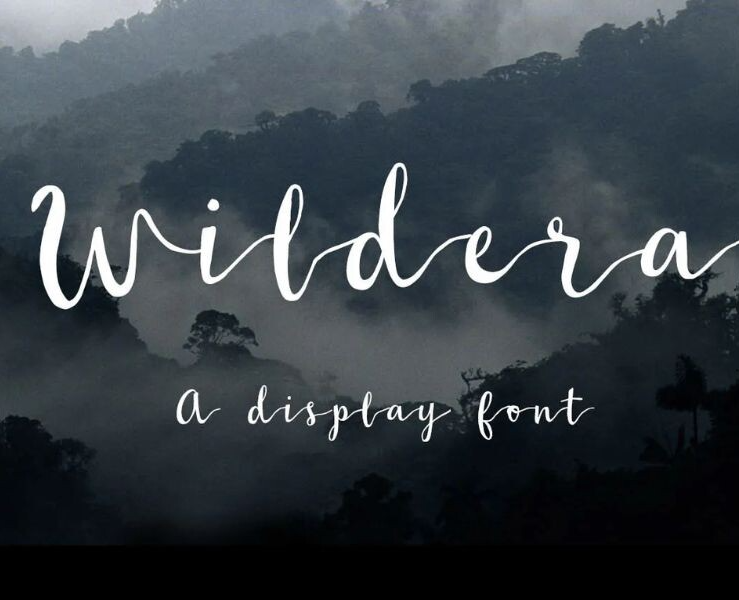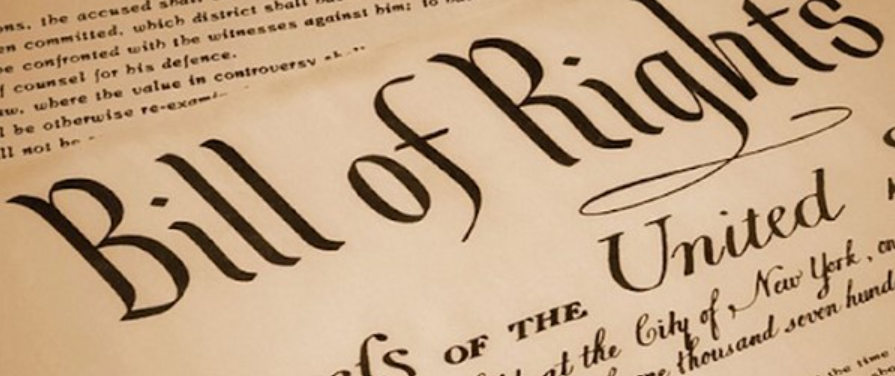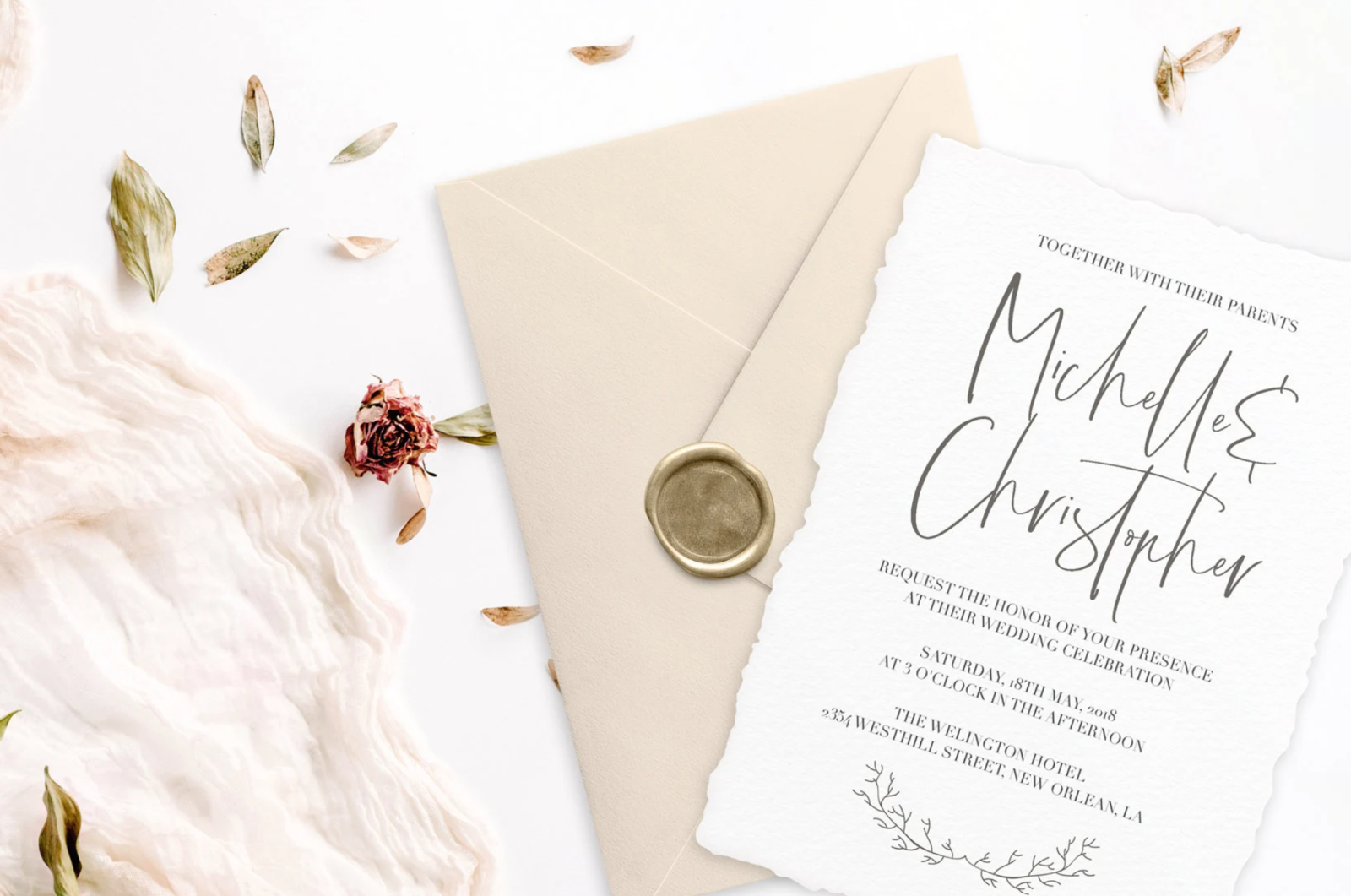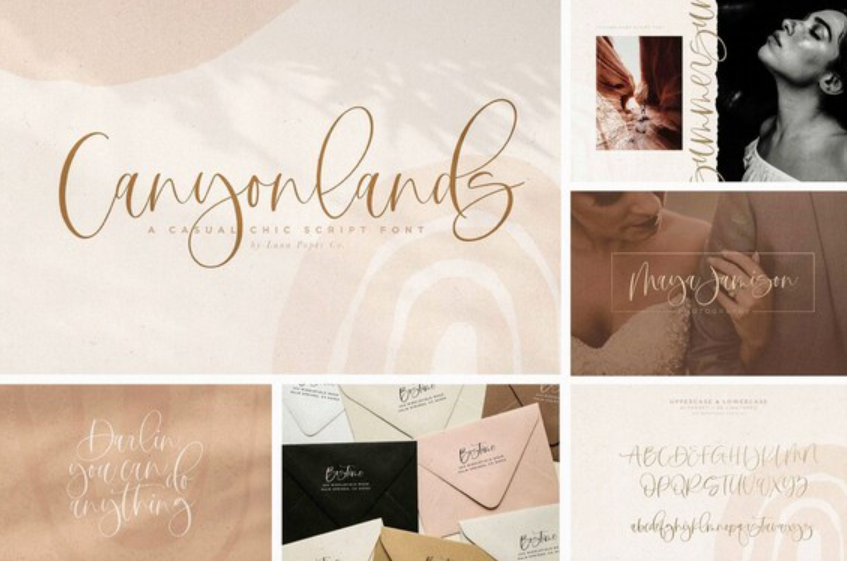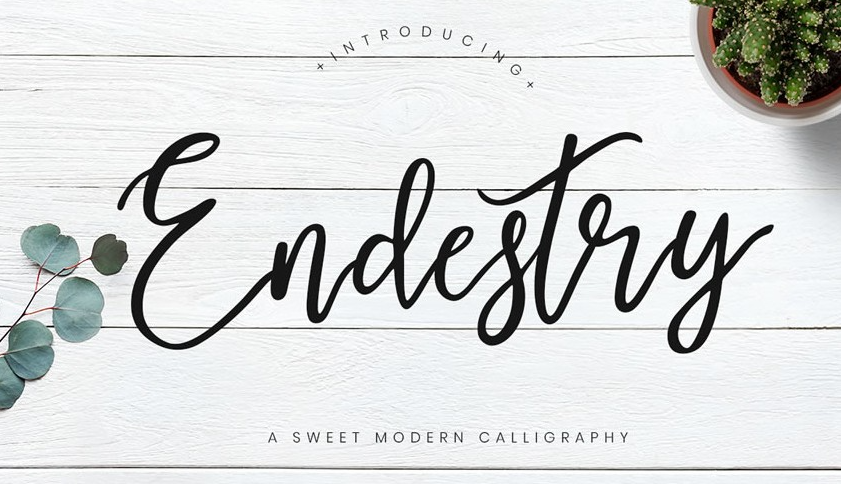
Khám Phá Font Chữ Calligraphy: Nghệ Thuật Ẩn Chứa Trong Từng Đường Nét
Bài viết sẽ mở ra hành trình khám phá về font chữ Calligraphy, giải mã nguồn cảm hứng nghệ thuật và cách mà từng nét chữ mang đậm giá trị sáng tạo, biến mỗi thiết kế thành một tác phẩm nghệ thuật độc đáo.
Font chữ không chỉ là công cụ truyền tải thông điệp mà còn là yếu tố nghệ thuật góp phần tạo nên cảm xúc và sự ấn tượng mạnh mẽ. Trong số rất nhiều phong cách font chữ hiện nay, Calligraphy – hay còn gọi là chữ thư pháp nghệ thuật đã và đang chiếm một vị trí đặc biệt vừa thể hiện nét tinh tế, vừa mang đến sự sang trọng cho các thiết kế. Bài viết dưới đây sẽ cùng bạn khám phá font chữ Calligraphy để tạo nên những thiết kế ấn tượng và chuyên nghiệp. Cùng tìm hiểu nhé!
1. Tìm hieur về font chữ Calligraphy
1.1. Định nghĩa
Font chữ Calligraphy hay còn gọi là chữ thư pháp nghệ thuật, là loại font mang phong cách viết tay với đường nét mềm mại, uyển chuyển và thanh lịch. Điểm đặc trưng của Calligraphy chính là sự tự nhiên trong cách vẽ nét chữ, thường được lấy cảm hứng từ nghệ thuật viết tay truyền thống của các nền văn hóa khác nhau. Mỗi chữ cái được tạo ra không hoàn toàn đồng nhất như các font số học truyền thống, mà mang đậm dấu ấn cá nhân của người nghệ sĩ, thể hiện sự tinh tế, sáng tạo và nghệ thuật.
So với các loại font chữ khác như sans-serif hay serif, Calligraphy nổi bật với nét nghệ thuật riêng biệt. Trong khi các font sans-serif thường được sử dụng cho thông tin hiện đại, gọn gàng, còn font Calligraphy lại hướng tới sự mềm mại, trữ tình và mang tính thủ công. Sự khác biệt này giúp Calligraphy trở thành lựa chọn lý tưởng cho các dự án cần tạo cảm giác sang trọng và tinh tế, chẳng hạn như thiệp mời cưới, logo thương hiệu cao cấp hay tiêu đề các ấn phẩm nghệ thuật.
1.2. Lịch sử hình thành của font chữ Calligraphy
Xuất phát từ nghệ thuật viết tay truyền thống của các nền văn hóa lớn như Trung Hoa, Ấn Độ hay phương Tây, Calligraphy từ lâu đã được tôn vinh như một hình thức nghệ thuật đòi hỏi sự tinh xảo và kiên nhẫn. Ở phương Đông, nghệ thuật thư pháp đã có từ hàng ngàn năm trước, với những nét chữ đầy uyển chuyển và linh hoạt được xem là biểu hiện của tâm hồn người viết. Các danh nhân, triết gia, họa sĩ cổ truyền không chỉ dừng lại ở việc truyền đạt thông tin mà còn truyền tải những giá trị tinh thần sâu sắc qua từng nét chữ.
Ngược lại, ở phương Tây, font chữ Calligraphy cũng phát triển mạnh mẽ qua các thời kỳ từ trung cổ cho đến thời kỳ Phục Hưng và hiện đại. Các nghệ nhân đã biến những nét chữ tay đơn giản thành nghệ thuật sống động, mang đậm phong cách cá nhân và cảm hứng sáng tạo riêng biệt. Sự giao thoa giữa văn hóa Đông – Tây đã tạo ra nhiều phong cách Calligraphy đa dạng, từ cổ điển đến hiện đại, từ trữ tình, nhẹ nhàng cho đến táo bạo, phá cách.
1.3. Đặc điểm nhận diện
Những đặc điểm nổi bật giúp nhận diện font chữ Calligraphy bao gồm:
Đường nét mềm mại: Mỗi nét chữ đều được cẩn thận thể hiện với sự uốn lượn, tạo nên cảm giác mềm mại và tự nhiên.
Tính nghệ thuật: Mỗi đường nét, mỗi chi tiết nhỏ đều mang đến giá trị nghệ thuật riêng biệt, khiến chữ trở nên độc đáo và khác lạ.
Biến tấu đa dạng: Không giống như các font số học, Calligraphy luôn thể hiện sự khác biệt nhỏ trong mỗi chữ cái, tạo nên vẻ đẹp “không hoàn hảo” nhưng đầy cảm xúc.
Ứng dụng đặc thù: Do nét chữ thường được tạo ra với hương vị nghệ thuật mạnh mẽ, Calligraphy thích hợp cho những thiết kế cần làm nổi bật thông điệp về sự trang nhã, tinh tế và độc đáo.
2. Ưu điểm và nhược điểm của font chữ Calligraphy
2.1. Ưu điểm của font chữ Calligraphy
Khi được áp dụng đúng cách, font chữ Calligraphy mang lại nhiều lợi ích cho thiết kế. Dưới đây là một số ưu điểm tiêu biểu:
Tạo sự sang trọng và độc đáo:
Font chữ Calligraphy giúp tạo ra sự ấn tượng mạnh mẽ ngay từ cái nhìn đầu tiên. Nét chữ mềm mại, tinh tế và đầy nghệ thuật làm cho các thiết kế trở nên sang trọng, phù hợp với những thương hiệu cao cấp hoặc các dịp đặc biệt như đám cưới, lễ kỷ niệm.
Mang đến tính nghệ thuật cao:
Với nguồn gốc từ nghệ thuật thư pháp truyền thống, Calligraphy không chỉ là font chữ mà còn là tác phẩm nghệ thuật. Sự tinh tế trong từng nét vẽ giúp truyền tải một thông điệp về sự sáng tạo, tinh thần và thậm chí cả cảm xúc của người thiết kế.
Phù hợp với các thiết kế tiêu đề và điểm nhấn:
Nhờ vào sự đẹp mắt và nổi bật của Calligraphy, các thiết kế sử dụng loại font này làm tiêu đề hoặc điểm nhấn sẽ thu hút sự chú ý của người xem một cách nhanh chóng. Điều này đặc biệt có lợi khi bạn muốn truyền tải thông điệp hoặc tạo cảm giác đầu tiên ấn tượng cho người nhận.
2.2. Nhược điểm và hạn chế của font chữ Calligraphy
Tuy mang lại nhiều điểm mạnh, nhưng font chữ Calligraphy cũng tồn tại một số hạn chế cần cân nhắc khi áp dụng:
Độ dễ đọc không cao:
Do sự mềm mại và nghệ thuật của các nét chữ, font Calligraphy thường không phù hợp cho các đoạn văn bản dài hoặc ở kích thước nhỏ. Việc sử dụng trong văn bản mượt mà có thể gây khó khăn cho người xem, đặc biệt là khi độ tương phản không đủ cao.
Tóm lại, font chữ Calligraphy mang đến một vẻ đẹp nghệ thuật đặc biệt giúp sản phẩm thiết kế trở nên sang trọng và tinh tế. Tuy nhiên, để tối ưu hóa lợi ích của nó, bạn cần cân nhắc đến các yếu tố như tính dễ đọc, sự kết hợp hài hòa với các phần tử khác trong thiết kế, và đặc biệt là đảm bảo quyền sử dụng hợp pháp. Calligraphy, dù có những hạn chế nhất định, nhưng nếu được xử lý khéo léo sẽ là “bí quyết” giúp bạn chinh phục thị trường thiết kế cạnh tranh ngày nay.